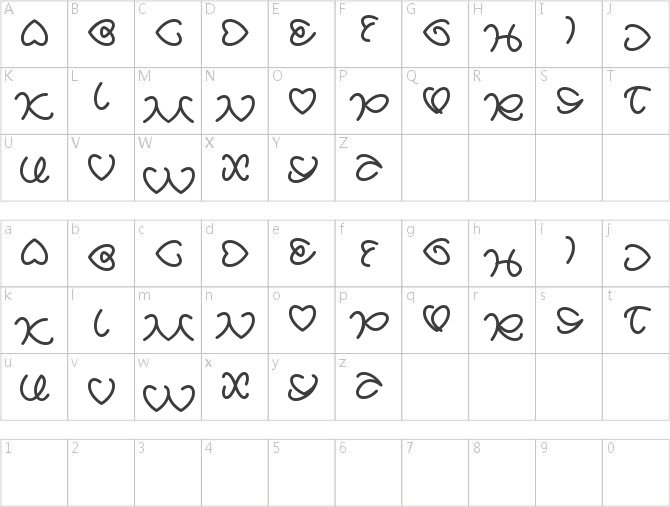
ALL ABOUT LOVE 詳情頁
字體名稱: ALL ABO
ALL ABOUT LOVE
ALL ABOUT LOVE介紹
ALL ABOUT LOVE字體字庫是一款讓人賞心悅目、百看不厭的英文字體,適合各類廣告和產品包裝設計應用,字體大小0.03MB,格式為ttf字體,上傳用戶是浪跡天涯,作者/版權方為未知